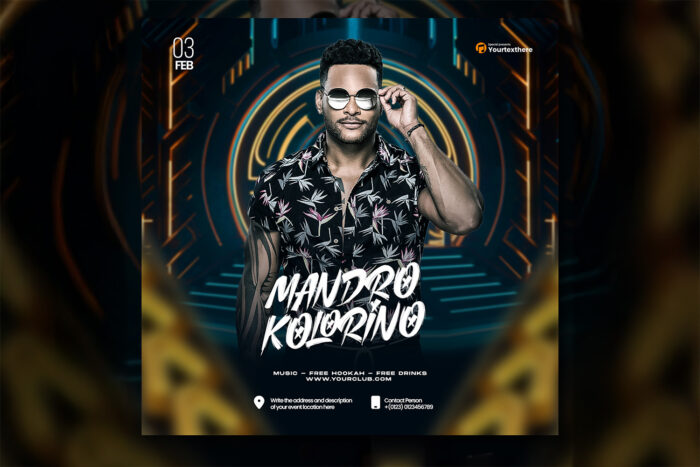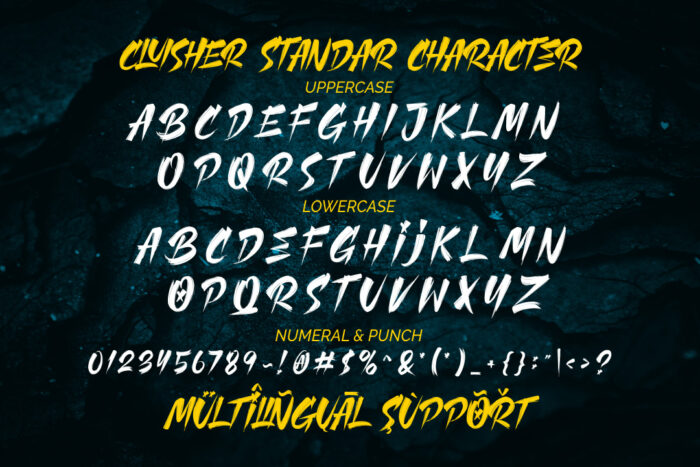
DVN Cluisher Brush Việt hóa – Font chữ Brush phá cách
Cluisher Brush là một font chữ được thiết kế với phong cách viết tay mạnh mẽ và sắc nét, mang đến cảm giác năng động và phá cách. Các đường nét của font này được tạo ra với sự kết hợp giữa những nét cọ tự do và các cạnh sắc, thể hiện rõ sự mạnh mẽ và sáng tạo. Các ký tự lớn, đậm, và mang hơi hướng graffiti, phù hợp với các thiết kế cần tạo điểm nhấn, như poster sự kiện, tiêu đề, bìa sách, hoặc logo.
Phần highlight của font là sự chuyển đổi màu gradient từ trắng sang vàng và cam, tạo nên sự tương phản bắt mắt và thu hút sự chú ý ngay lập tức. Điều này làm cho Cluisher Brush nổi bật trong các ứng dụng đồ họa hoặc truyền thông xã hội. Font chữ này cũng được Việt hóa hoàn toàn, giúp người dùng có thể sử dụng dễ dàng với tiếng Việt mà không gặp trở ngại về việc hiển thị dấu.